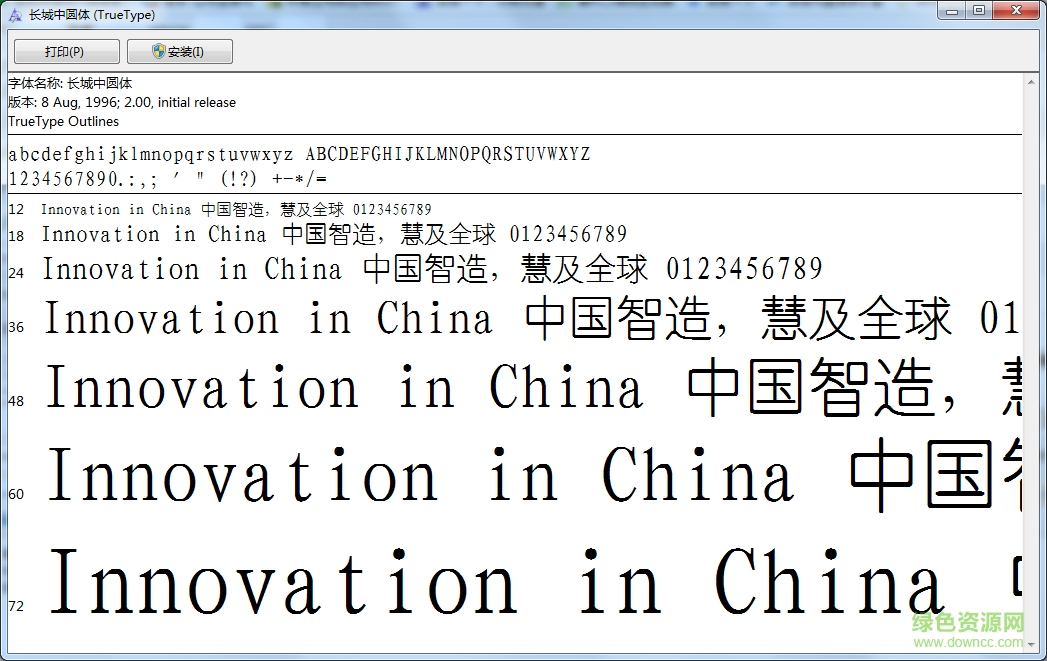
ggtr00m
ggtr00m是什么字體?ggtr00m字體是一款筆畫圓潤的長城中圓體,該字體沒有什么線條粗細(xì)變化,形態(tài)自然,流暢灑脫,十分漂亮,歡迎大家免費(fèi)下載!
圓體介紹
一種由黑體演變而來的字體。大概出現(xiàn)于清末。拐角處、筆畫末端為圓弧狀。字體清晰、端正、嚴(yán)肅,適合于報(bào)紙大字頭、圖書封面、招牌、廣告、網(wǎng)站標(biāo)題的制作。變體為幼圓體、琥珀體等。
ggtr00m字體